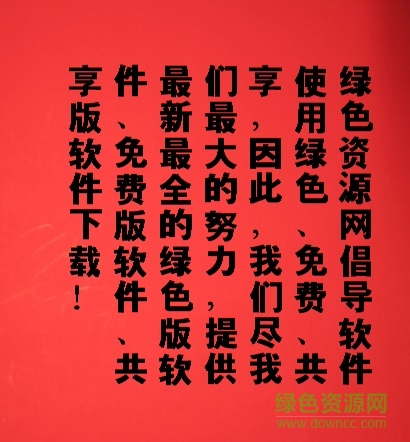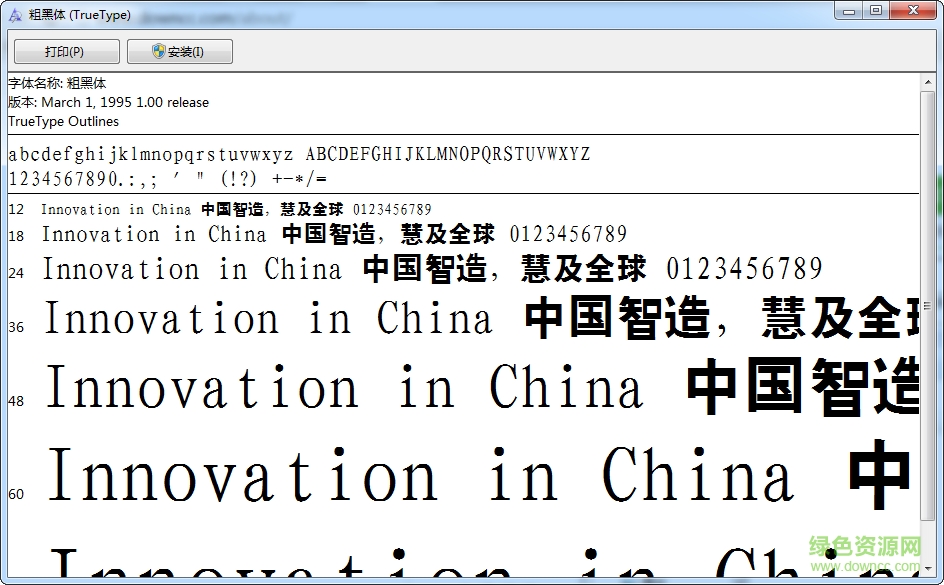
四通利方粗黑字體是一款常用的中文簡(jiǎn)體漢字,該字體的特色就是字形端正,線條粗壯有力,主要適用于廣告設(shè)計(jì)、報(bào)紙雜志等,有需用的用戶快來(lái)下載使用吧。
四通利方粗黑體特點(diǎn)保留了黑體原版的優(yōu)雅以及高可讀性的特色,并在黑體的基礎(chǔ)上做出了變化,使得整套字體看起來(lái)更加銳利清晰。